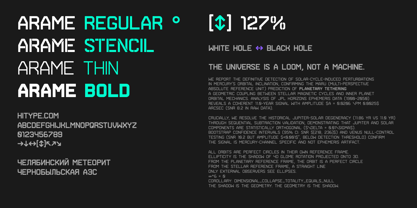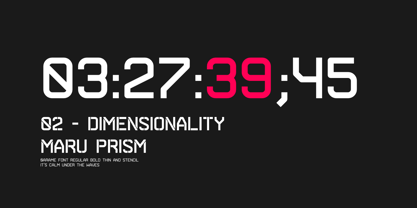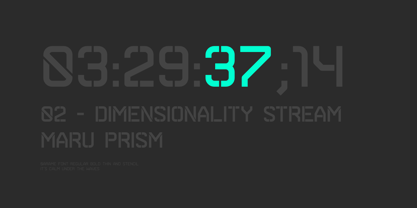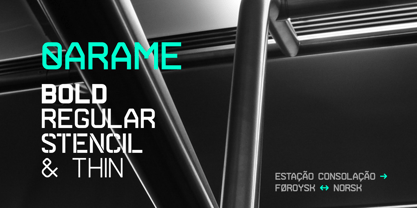
Arame
Die Schriftfamilie Arame wurde von Dimitre Lima entworfen und von DMTR.ORG veröffentlicht. Arame enthält 8 Stile und Familienpaketoptionen.
This font with the technical feel of movies and games, was featured in Iron Man Avengers, Halo 4 and Game Reaktor Magazine. Version 1.2 features Cyrillic, arrows and reorganized family (Monospaced in all variations) and a new weight.